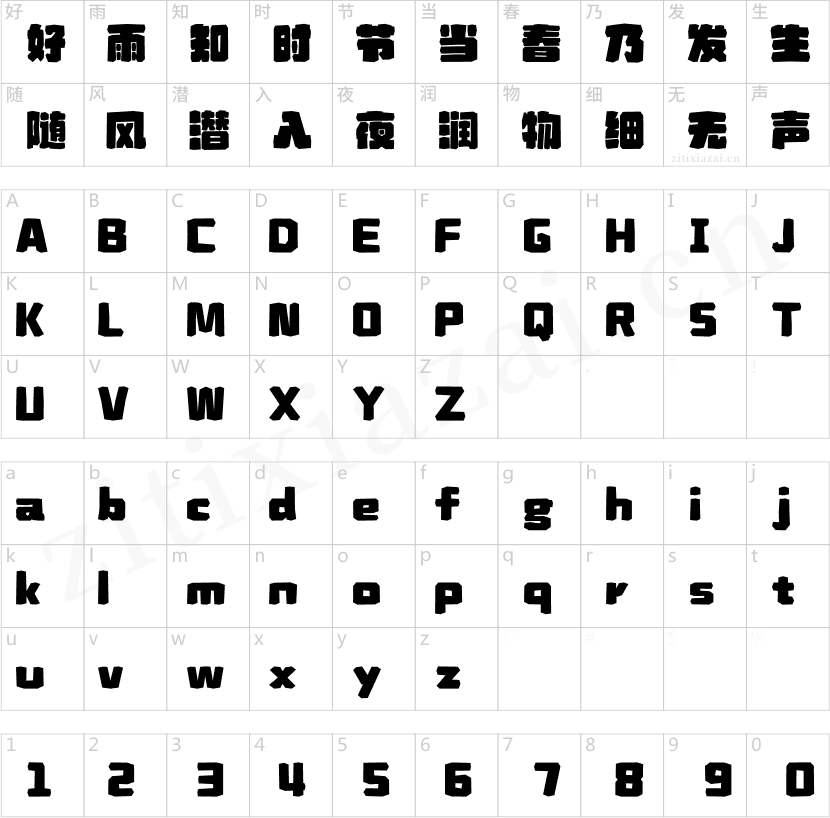
汉仪永字探月
汉仪永字探月,这款字体结构工整、笔画清晰,兼顾美观与易读性,适用于标题、正文、海报、包装、LOGO 等多种场景。字形优雅稳定,风格百搭耐看,适配日常排版与创意设计,让文字呈现更舒适、更具质感。汉仪永字探月一笔一画,皆是细节,以均衡的比例、流畅的线条打造舒适视觉体验,字形端正大气,风格简约现代。无论是商业设计、品牌宣传还是日常排版,都能轻松驾驭,让文字更有格调与力量。汉仪永字探月字体下载。
• 字体说明:汉仪永字探月是一款由永字社创作的“重量级”标题字体,饱满的字形、坚实的笔画,如同巨大的撞击坑和坚硬的月岩,带来探索月球表面的视觉体验。这款字体活泼有趣,排版效果极具块面感,有着强烈的视觉冲击力,适合标题字体以及较大字号较短文本的排版,应用于趣味科普、少儿读物、绘本漫画等各类场景。